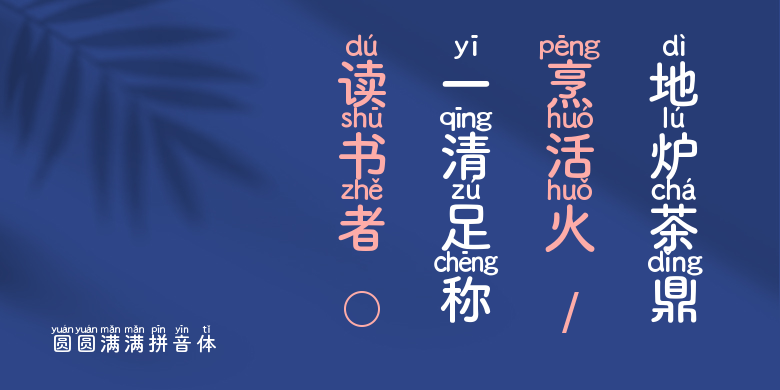
圆圆满满拼音体
圆圆满满拼音体,这款字体结构工整、笔画清晰,兼顾美观与易读性,适用于标题、正文、海报、包装、LOGO 等多种场景。字形优雅稳定,风格百搭耐看,适配日常排版与创意设计,让文字呈现更舒适、更具质感。圆圆满满拼音体一笔一画,皆是细节,以均衡的比例、流畅的线条打造舒适视觉体验,字形端正大气,风格简约现代。无论是商业设计、品牌宣传还是日常排版,都能轻松驾驭,让文字更有格调与力量。圆圆满满拼音体字体下载。